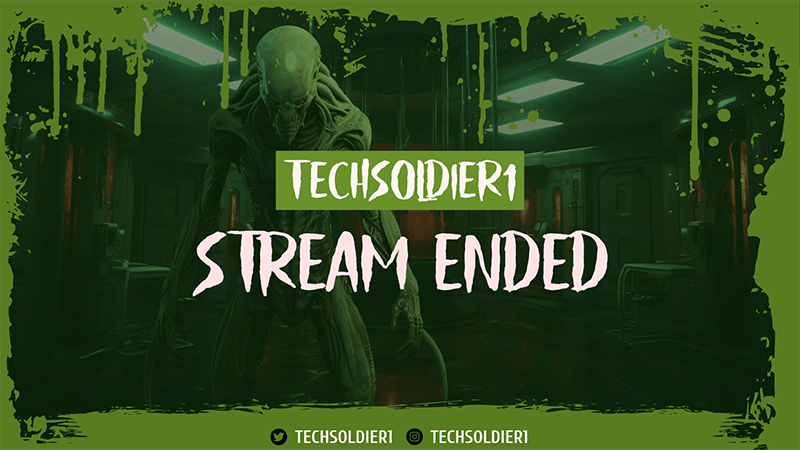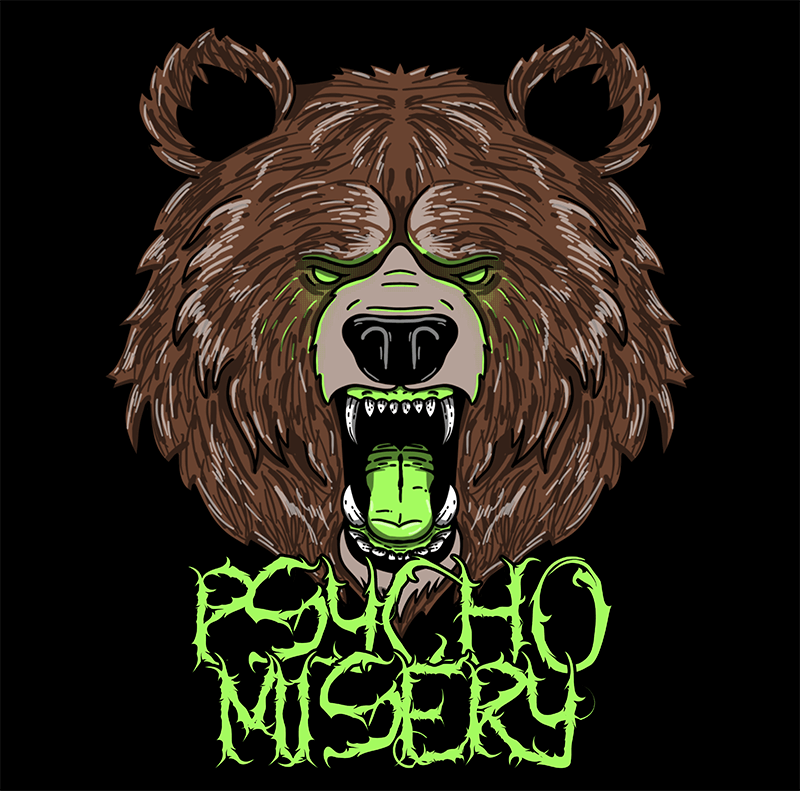
🎃 Cadılar Bayramı Yazı Tipleriyle Ürkütücü Yaratıcılığı Ortaya Çıkarın
Yaprakların rengi değiştikçe ve havaya bir ürperti yayıldıkça, ürkütücülük mevsimi üzerimize çöküyor. Dünya çapında kutlanan sevilen bir tatil olan Cadılar Bayramı, yaratıcı yönünüzü açığa çıkarmak için heyecan verici bir fırsat sunuyor. Korkunç dekorasyonlardan ürkütücü davetiyelere kadar Cadılar Bayramı estetiği, şenliklerin tonunu belirlemede çok önemli bir rol oynuyor. Bu unutulmayacak tatilin ruhunu yakalamanıza yardımcı olabilecek önemli unsurlardan biri deCadılar Bayramı yazı tiplerinin kullanılmasıdır .
Bu yazıda Cadılar Bayramı yazı tiplerinin büyüleyici dünyasına dalacağız, Cadılar Bayramı tasarımlarınıza nasıl ürkütücü bir öz katacağınızı, mevcut çeşitli Cadılar Bayramı yazı tipi stillerini ve bu yazı tiplerini ücretsiz olarak nerede bulabileceğinizi keşfedeceğiz!
Tasarımlarınıza Cadılar Bayramı Stili Vermek İçin 5 İpucu
Tipografi, ruh hallerini anında aktarabilen ve duyguları uyandırabilen güçlü bir tasarım aracıdır. Cadılar Bayramı temalı tasarımlar söz konusu olduğunda doğru yazı tipi, hedef kitlenizi gizem ve entrikalarla dolu bir dünyaya taşıyabilir. Yazı tiplerini kullanarak tasarımlarınıza benzersiz bir Cadılar Bayramı stili kazandıracak bazı ipuçlarını burada bulabilirsiniz.
1. Doğru Yazı Tipini Seçin
Ürkütücü bir hava yayan yazı tiplerini tercih edin. Keskin kenarlara, seriflere ve dekoratif unsurlara sahip gotik yazı tipleri, anında ürkütücü bir ortam yaratabilir. "Chiller", "Nosferotica" ve "Gotham Nights" gibi yazı tipleri, Cadılar Bayramı'ndan ilham alan tasarımlar için mükemmel seçimlerdir.
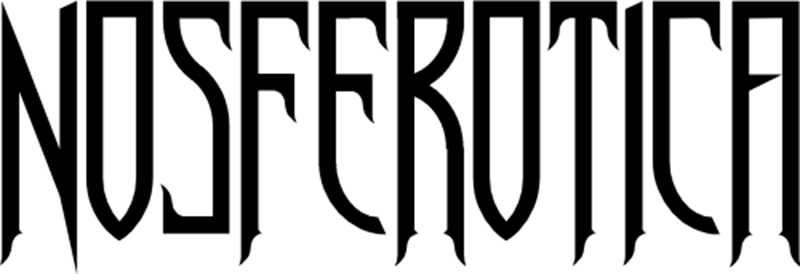
2. Bitişik Harfler ve Kelimelerle Oynayın
Ligatür, iki veya daha fazla harfin tek bir kelime oluşturacak şekilde birleştirilmesiyle oluşur .
Bazı Spooky Halloween yazı tipleri, tasarımlarınıza ilginç bir dokunuş katan benzersiz bitişik harfler ve kelimeler sunar. Metninizde özel karakterler olarak kullanılabilecek yarasalar, örümcekler, balkabakları veya diğer Cadılar Bayramı temalı karakterleri içeren yazı tiplerini arayın.
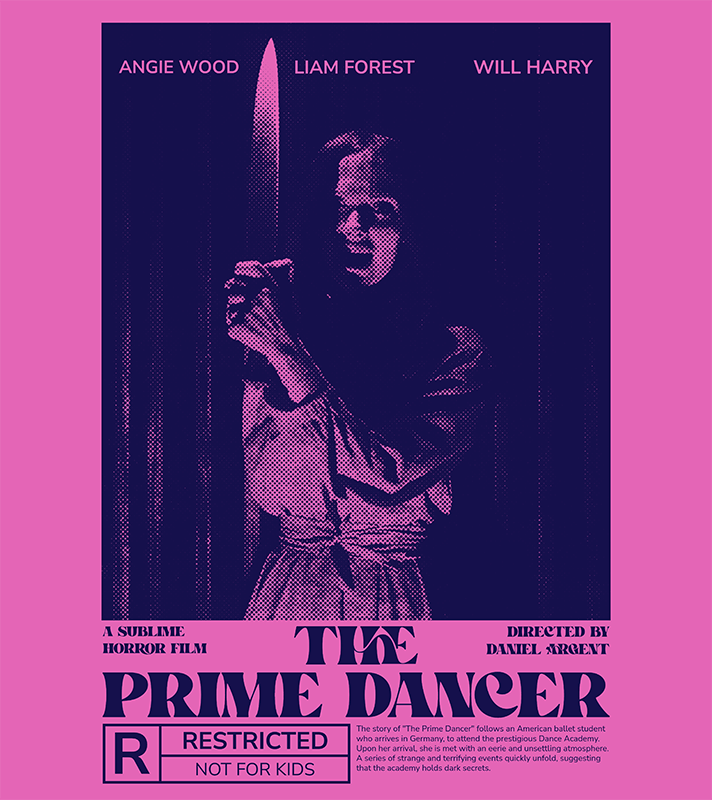
3. Harf Aralığını ve Karakter Aralığını Ayarlayın
Karakter aralığı , tek tek harfler veya karakterler arasındaki boşluktur .
Metninizin görsel çekiciliğini artırmak için harf aralığı ve karakter aralığını deneyin. Hafifçe uzatılmış veya yoğunlaştırılmış harf biçimleri, genel perili atmosfere katkıda bulunabilir.
4. Dokuyu Birleştirin
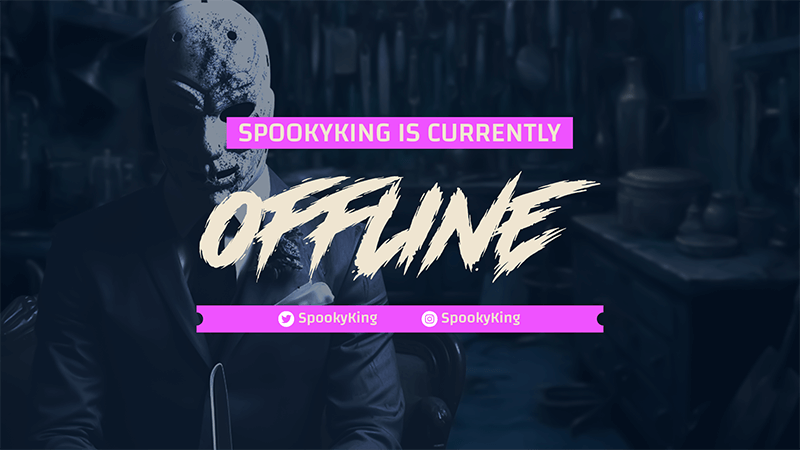
Birçok korkutucu yazı tipi, tasarımlarınıza vintage ve ürkütücü bir görünüm kazandırabilecek dokulu veya eskitilmiş varyasyonlarla birlikte gelir. Bu dokular eskimiş parşömenleri veya unutulmuş bir kitabın yıpranmış görünümünü simüle edebilir.
5. Yazı Tiplerini Dikkatli Bir Şekilde Karıştırın
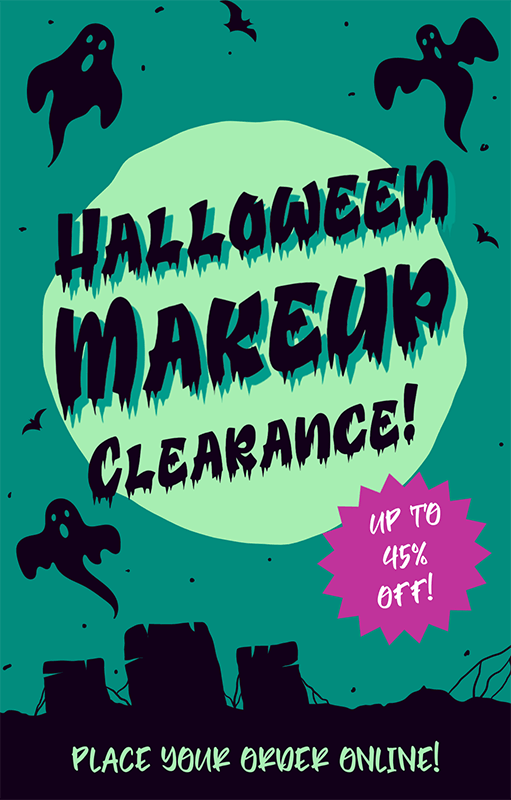
Derinlik ve kontrast eklemek için farklı yazı tiplerini bir tasarımda birleştirmeyi düşünün. Cesur, göz alıcı bir başlık yazı tipini daha sade bir gövde yazı tipiyle eşleştirmek, dinamik bir görsel hiyerarşi oluşturabilir.
Cadılar Bayramı Yazı Tipi Stilleri Mevcuttur
Yazı tipleri dünyası, çeşitli zevklere ve tasarım tercihlerine hitap eden çeşitli stillerden oluşan bir hazinedir. İster klasik bir korku filmi havası, ister eğlenceli ve çocuk dostu bir görünüm, ister gotik bir zarafet hedefliyor olun, vizyonunuza uygun bir yazı tipi stili mutlaka vardır.
Ürpertici ve Çarpık
Bu yazı tipleri Cadılar Bayramı'nın rahatsız edici ve ürkütücü yönlerini temsil ediyor. Karakterler çarpık, çarpık veya başka bir dünyaya ait bir aurayla damlayan görünebilir. "Creepster", "Distorted Faith" ve "Toxic Type" gibi yazı tipleri bu kategoriye girer.
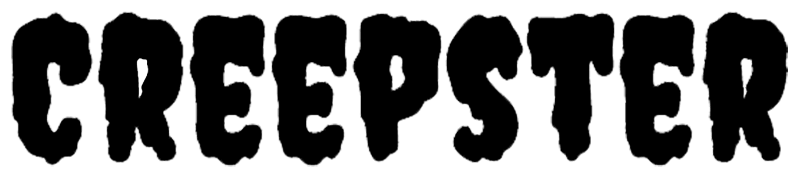
Sevimli ve Eğlenceli
Aile dostu Cadılar Bayramı tasarımları için ideal olan sevimli ve eğlenceli yazı tipleri, dost canlısı canavarlar, gülümseyen balkabakları ve tuhaf karakterler içerir. Bu yazı tipleri, tatilin ürkütücü kökleri ile neşeli bir yaklaşım arasında bir denge kuruyor. Örnekler arasında "Cadılar Bayramı Örümceği", "Şeker mi Şaka mı" ve "Boo Yah" yer alıyor.
Gotik ve Zarif
Daha sofistike ve gotik bir atmosfer hedefliyorsanız bu kategorideki yazı tipleri en iyi seçeneğinizdir. Karmaşık ayrıntılar ve süslü süslemelerle bu yazı tipleri, karanlık bir romantizm duygusu uyandırıyor. "Gothicus", "Vampiro One" ve "Victoria Parlour" gibi yazı tipleri bu tarzın örnekleridir.
Korku Filmi Ortamları
Klasik korku filmlerinin özünü yansıtmak isteyenler için sinema başyapıtlarının tüyler ürpertici başlıklarını yansıtan yazı tipleri bir zorunluluktur. "Horror Show", "Scream Real" ve "Psycho" gibi yazı tiplerini düşünün.